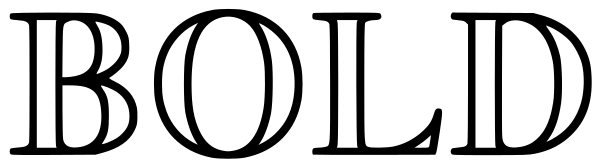
Ажурный шрифт
Ажурный шрифт[1] (англ. Blackboard bold, Double-struck) — тип шрифта, в котором у символов удвоены определённые штрихи. Буквы в ажурном шрифте часто употребляются в математике для обозначения важных множеств, как например ℝ для вещественных чисел[2].
Ажурный шрифт происходит из попыток написать жирный на доске. В типографику ажурный шрифт ввёл, вероятно, учебник Ганнинга и Росси по функциям комплексного переменного (1965).
Кодировка
Хотя в TeX нет возможности вывести символы в ажурном шрифте, ажурный шрифт присутствует в расширении AMS Fonts package (amsfonts) Американского математического общества, где он выставляется с помощью кода \mathbb. Таким образом, символ ℝ () кодируется как \mathbb{R}[1]. Расширение amsfonts также присутствует в AMS-LaTeX.
Расширения txfonts и pxfonts для LaTeX различают два типа ажурного шрифта, кодируемых как \mathbb и \varmathbb соответственно. bbm также поддерживает ажурный шрифт без засечек (\mathbbmss) и моноширинный ажурный шрифт (\mathbbmtt). Расширение mathbbol содержит разные скобки и греческий алфавит в ажурном шрифте, а mbboard — буквы греческого и еврейского алфавитов, знаки пунктуации, а также некоторые знаки валют. dsfont поддерживает шрифт, схожий с ажурным, в котором у каждой буквы удвоен только один штрих (\mathds)[3].
В Юникоде несколько часто встречающихся символов в ажурном шрифте (ℂ, ℍ, ℕ, ℙ, ℚ, ℝ и ℤ) закодированы в блоке Буквоподобные символы (англ. Letterlike Symbols, U+2100—214F) Основной многоязычной плоскости (BMP) под названиями вида double-struck capital c[4]. Остальным присвоены кодовые позици от U+1D538 до U+1D550 для заглавных, от U+1D552 до U+1D56B для строчных букв и с U+1D7D8 по U+1D7E1 для цифр в Дополнительной многоязычной плоскости (SMP), блоке Математические буквы и цифры (англ. Mathematical Alphanumeric Symbols, U+1D400—1D7FF)[5].
Использование
В данной таблице представлены все закодированные в Юникоде символы в ажурном шрифте и их возможные варианты употребления в математике.
𝔸 | Алгебраические числа[6] | |
𝔹 | Булева область[7], — -мерный шар[8] | |
ℂ | Комплексные числа[9], или - Расширенная комплексная плоскость[10] | |
𝔻 | — -мерный круг[11] | |
ⅅ | Может обозначать дифференциал[4] | |
ⅆ | Может обозначать дифференциал[4] | |
𝔼 | — -мерное Евклидово пространство[12] | |
ⅇ | Может обозначать число e[4] | |
𝔽 | Поле[2], — конечное поле порядка [13] | |
𝔾 | Гауссовы целые числа[2] | |
ℍ | Кватернионы[14], верхняя полуплоскость[15], — Геометрия Лобачевского[16] | |
𝕀 | Целые числа[17], — -мерная единичная матрица[18] | |
ⅈ | Может обозначать мнимую единицу[4] | |
ⅉ | Может обозначать мнимую единицу[4] | |
ℕ | Натуральные числа[19]. Натуральные числа с нулём {0, 1, 2…} могут обозначаться как (чаще в западных книгах по компьютерной математике), , . | |
𝕆 | Октонионы[20] | |
ℙ | Простые числа[21], — -мерное вещественное проективное пространство[22] | |
ℚ | Рациональные числа (от нем. Quotient «частное»)[23], — положительные рациональные числа[24], — алгебраические числа[25], — p-адические числа[26] | |
ℝ | Вещественные числа[27], — положительные вещественные числа[28], — отрицательные вещественные числа[29], — -мерное Евклидово пространство[12], — расширенная числовая прямая[30] | |
𝕊 | — -мерная сфера[31] | |
𝕋 | — -мерный тор[2] | |
𝕍 | Векторное пространство[32] | |
ℤ | Целые числа[33], — положительные целые числа[34], — отрицательные целые числа[35], — неотрицательные целые числа[36] | |
⅀ | Сумма | |
𝟘 | Наименьший элемент решётки | |
𝟙 | Наибольший элемент решётки | |
Также незакодированная в Юникоде ажурная греческая буква мю может использоваться для обозначения групповой схемы корней -й степени из единицы[37].